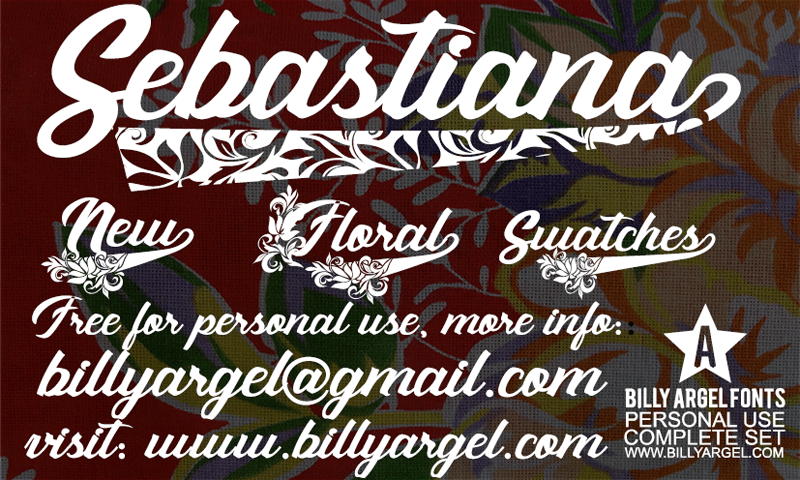
Sebastiana Font – Download Grátis
A fonte ‘Sebastiana Font’ é uma elegante obra-prima para artistas de letras aquarelas e designers que valorizam os detalhes. Desenvolvida pelo designer Hamilton, essa fonte única tem características suaves e graciosas perfeitas para textos artísticos ou obras de arte digitais. Com o seu design minimalista e limpo, Sebastiana oferece uma variedade impressionante de estilo, combinando com várias tipografias e permitindo personalizações sutis. Para quem deseja explorar mais os recursos desta fonte, é possível adquirir um lote completo ou licenças comerciais direto no site oficial de Hamilton em billyargel.com. Para obter informações adicionais ou entrar em contato diretamente com o designer, visite . Além disso, você pode explorar ainda mais os outros recursos gráficos criados por Hamilton acessando seu site pessoal e sua página do Facebook em www.billyargel.com e http://www.facebook.com/billyargelfonts.